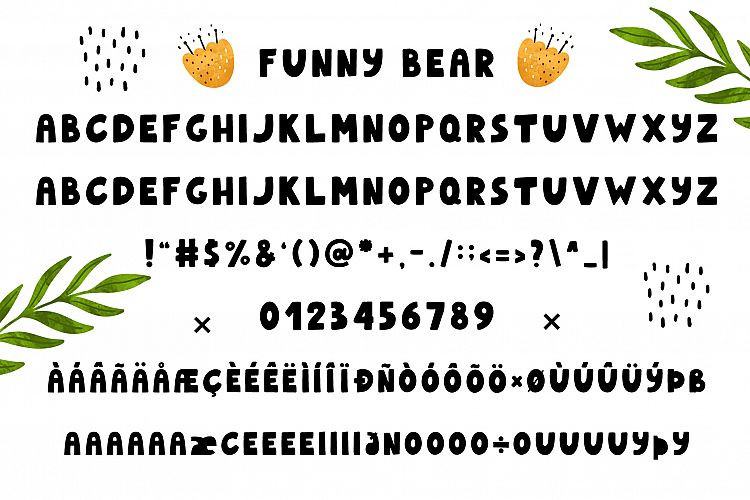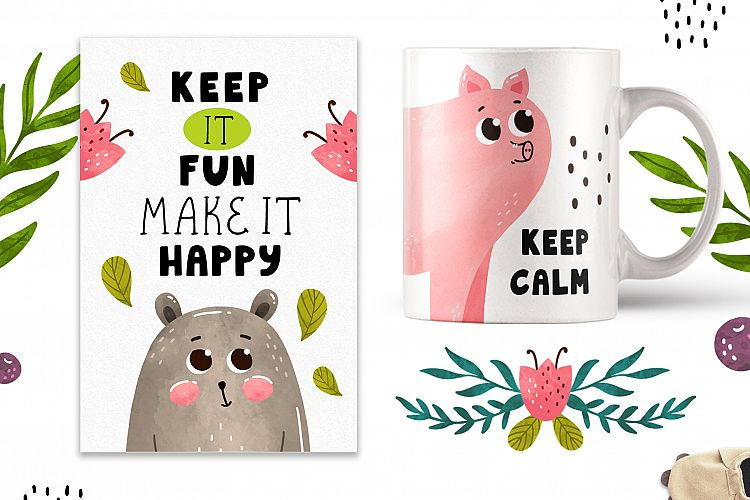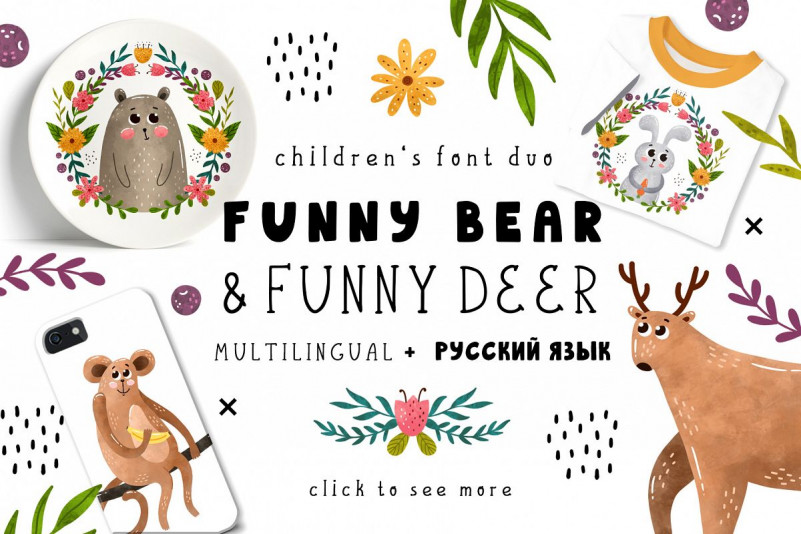
Funnybear & Funnydeer – Duo font
Funnybear & Funnydeer - Duo fontСпешу познакомить вас с удивительным и милым шрифтом duo-Funnybear и Funnydeer!Эти милые шрифты сделаны вручную и с большой любовью, особенно для ваших близких! Создайте свой собственный уникальный дизайн открыток, плакатов, пожеланий, приглашений, предметов интерьера, текстиля, ткани, брошюр, подарочной упаковки, значков и многого другого! Эти шрифты многоязычны! Кириллица также включена!